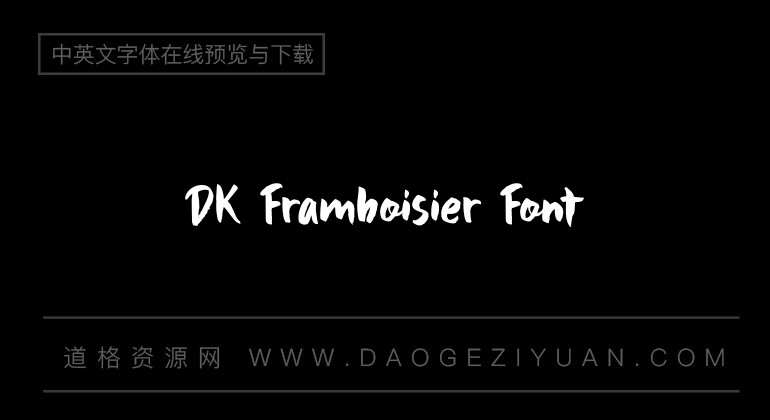
DK Framboisier Font 是一种手写风格的字体,有一些草拟的感觉。它由设计师Hanoded设计,由Dennis Ludlow发行。这种字体带有一些自然的笔画和手绘的感觉,因此非常适合用在具有手工和DIY感觉的设计项目中。 DK Framboisier Font 包含大写字母、小写字母、数字、标点符号和一些特殊字符。其字母的线条粗细不一,使得它看起来更加自然和有机。它的笔画也相对较大,使得它在大型设计中很容易阅读。 这种字体可以适用于多种设计项目,如海报、包装设计、品牌标识、手写信件等。如果你需要一种充满个性和独特性的字体,DK Framboisier Font 可以是你的一个很好的选择。内容介绍
DK Framboisier Font是一款非常不错的手写艺术字体,具有很好的视觉感,适合于文化类的宣传设计、商业类品牌的广告和产品包装设计以及个性化文字排版等较多场景。